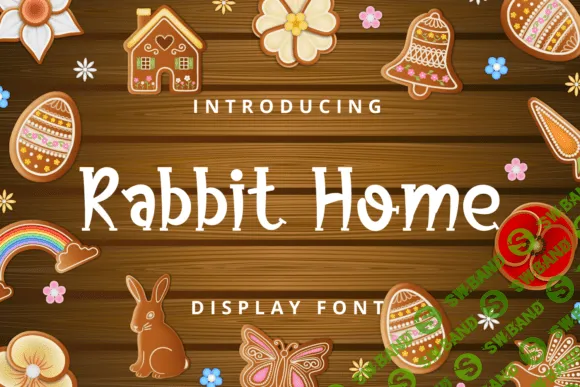
Название: Rabbit Home Font
Rabbit Home - дружественный шрифт для отображения.
Он воплощает в себе веселье, уникальность и подлинность.
Этот ослепительный шрифт превратит любую творческую идею в яркий образец!
Название: Rabbit Home Font
Rabbit Home - дружественный шрифт для отображения.
Он воплощает в себе веселье, уникальность и подлинность.
Этот ослепительный шрифт превратит любую творческую идею в яркий образец!